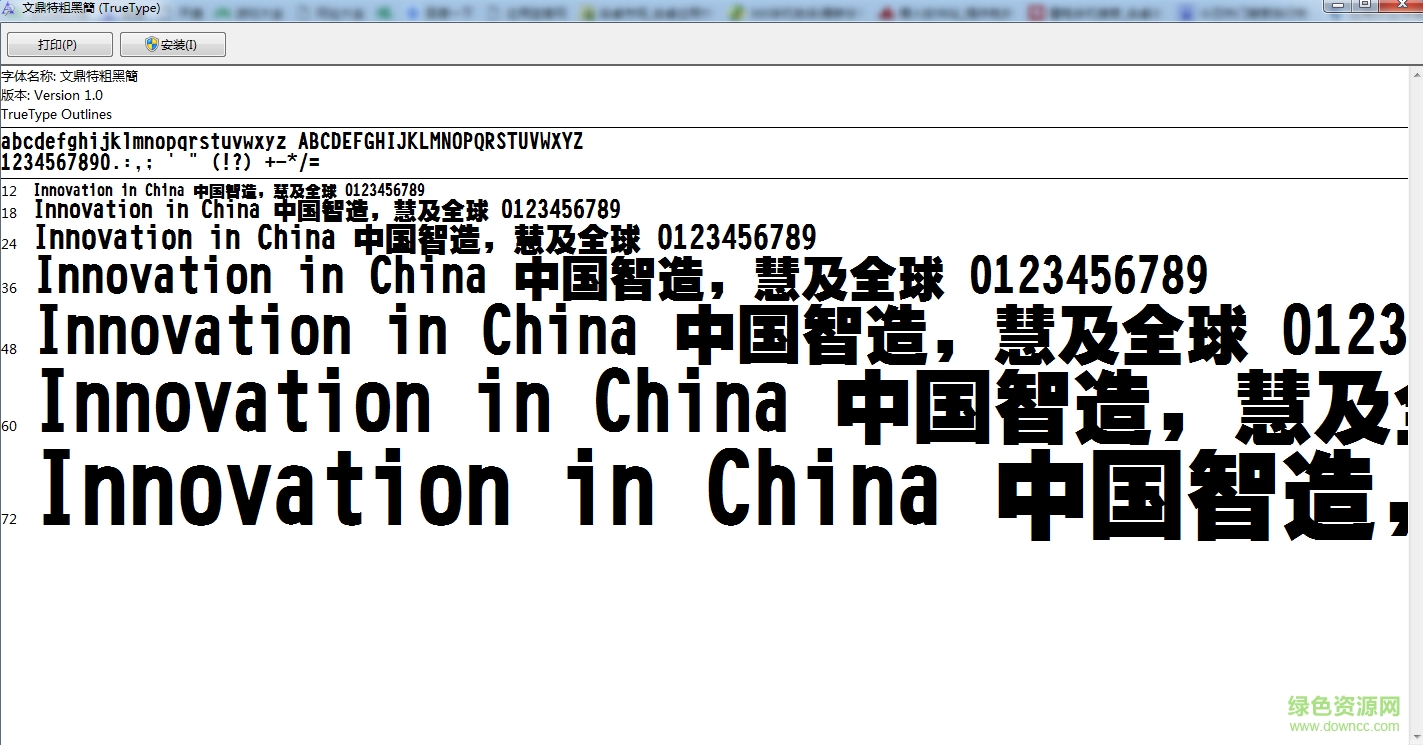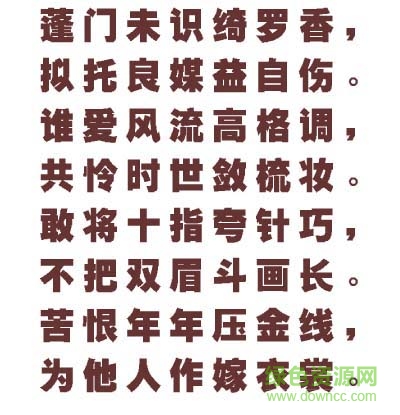
heitieg ultra gb(文鼎特粗黑簡)字體是一款異常醒目的字體,字型飽滿,氣勢雄健,這款字體同時支持中英文輸入,可用作文章標題、宣傳標語等,需要的小伙伴快來綠色資源網(wǎng)下載吧!
【文字的可識性】
文字的主要功能是在視覺傳達中向消費大眾傳達信息,而要達到此目的必須考慮文字的整體訴求效果,給人以清晰的視覺印象
【文字的視覺美感】
文字在視覺傳達中,作為畫面的形象要素之一,具有傳達感情的功能,因而它必須具有視覺上的美感,能夠給人以美的感受。人們對于作用其視覺感官的事物以美丑來衡量,已經(jīng)成為有意識或無意識的標準。
【文字設(shè)計的個性】
根據(jù)廣告主題的要求,極力突出文字設(shè)計的個性色彩,創(chuàng)造與眾不同的獨具特色的字體,給人以別開生面的視覺感受,將有利于企業(yè)和產(chǎn)品良好形象的建立。
【文字的適合性】
文字設(shè)計重要的一點在于要服從表述主題的要求,要與其內(nèi)容吻合一致,不能相互脫離,更不能相互沖突,破壞了文字的訴求效果。